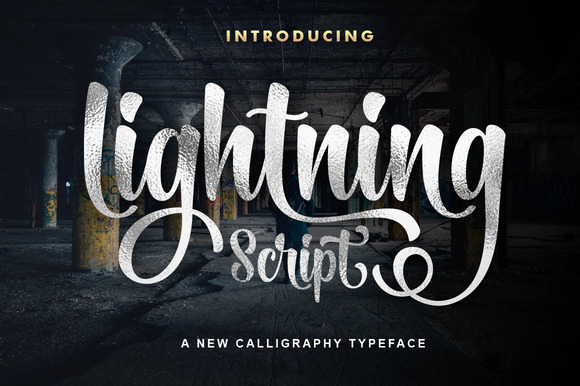
Lightning Script
หากคุณกำลังมองหาเนื้อหาคุณภาพสูงเช่น Lightning Script แพ็คเกจพรีเมียมนี้เป็นตัวเลือกที่ยอดเยี่ยมสำหรับโปรเจ็กต์สร้างสรรค์ของคุณ
ไม่ว่าคุณจะสร้างผลิตภัณฑ์ POD (Print on Demand) คำเชิญงานแต่งงาน หรือกราฟิกโซเชียลมีเดีย Lightning Script ก็เหมาะสมอย่างยิ่ง